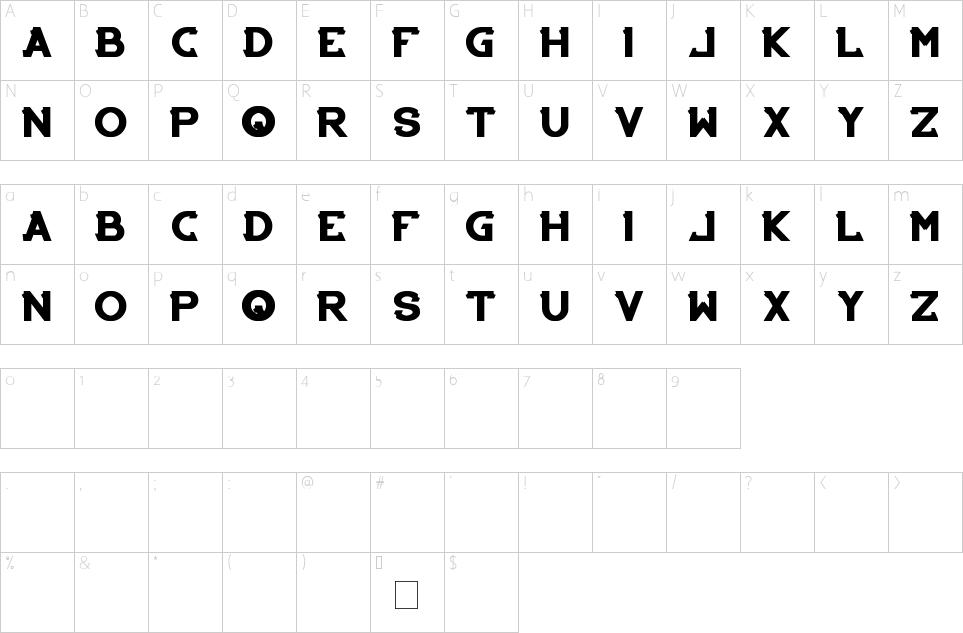
A fonte Arcade é uma escolha perfeita para designers em busca de um estilo que transmite energia e diversão. Desenhada por um artista desconhecido, ela reveste seus textos com linhas curvas e desenhos animados, certamente atraente para projetos como logomarcas, artigos de jornal e até mesmo para criar aqueles efeitos visuais atraentes em sites e blogs. Esta fonte foi projetada para ser usada tanto em sistemas Windows quanto em Mac, tornando-a uma opção versátil e conveniente para qualquer tipo de projeto. Com seu download de mais de 12.876 vezes, você pode garantir que está se beneficiando de uma fonte popular e de alta qualidade que certamente será uma grata surpresa para quem a usar.